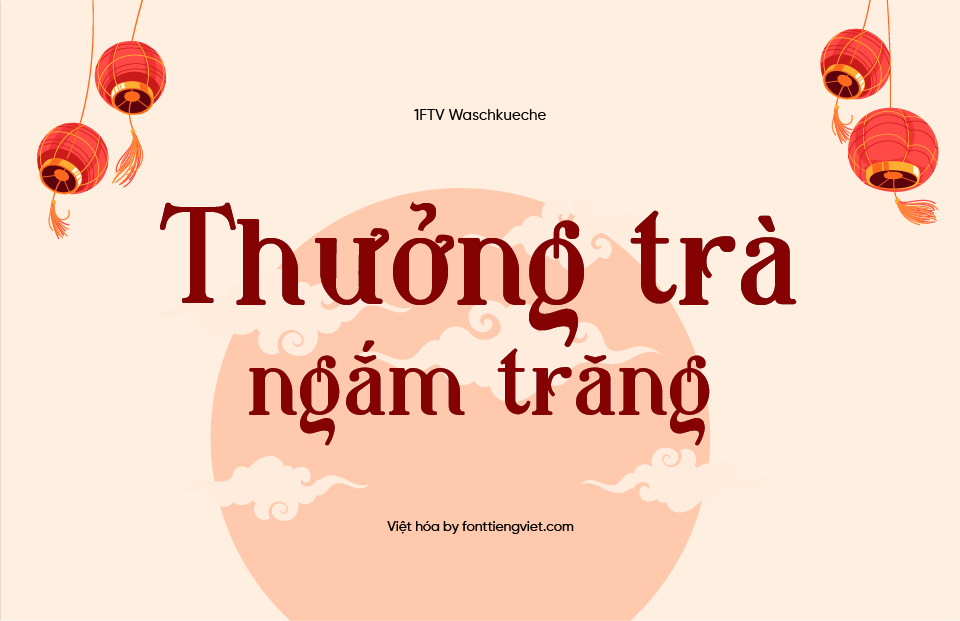
Font việt hóa 1FTV Waschkueche
Giới thiệu về Font việt hóa 1FTV Waschkueche
Trong thế giới đồ họa hiện đại, việc tìm kiếm một bộ Font Miễn Phí có phong cách hoài cổ nhưng vẫn đảm bảo tính ứng dụng cao là điều không hề dễ dàng. Font việt hóa 1FTV Waschkueche chính là giải pháp hoàn hảo cho những ai yêu thích vẻ đẹp của các bảng hiệu xưa cũ tại châu Âu. Được lấy cảm hứng từ những nét chữ viết tay thô mộc, bộ font này mang đến cảm giác gần gũi và ấm áp cho người xem.
Đặc điểm thiết kế nổi bật
Bộ Font việt hóa 1FTV Waschkueche sở hữu những đường nét mạnh mẽ nhưng không kém phần uyển chuyển. Các ký tự được chăm chút kỹ lưỡng để giữ được cái “hồn” của bản gốc, đồng thời được tối ưu hóa để hiển thị sắc nét trên cả màn hình kỹ thuật số và các ấn phẩm in ấn. Đây là lựa chọn lý tưởng cho các bạn học sinh khi thiết kế báo tường hoặc trang trí tập vở thêm phần sinh động.
Ứng dụng Font việt hóa 1FTV Waschkueche trong thực tế
Sáng tạo nội dung giáo dục
Với các thầy cô giáo, việc sử dụng Font việt hóa 1FTV Waschkueche giúp các bài giảng PowerPoint trở nên lôi cuốn hơn. Font chữ này hỗ trợ đầy đủ bảng mã tiếng Việt, giúp tránh lỗi hiển thị khi soạn thảo văn bản. Sự độc đáo của nó giúp học sinh dễ dàng tập trung vào các tiêu đề quan trọng trong bài học.
Trang trí và truyền thông
Ngoài môi trường học đường, font này còn được dùng rộng rãi trong thiết kế logo, menu quán cà phê hay các bìa sách mang phong cách vintage. Khả năng kết hợp linh hoạt với các tông màu trầm giúp tạo nên một không gian nghệ thuật đậm chất cổ điển.